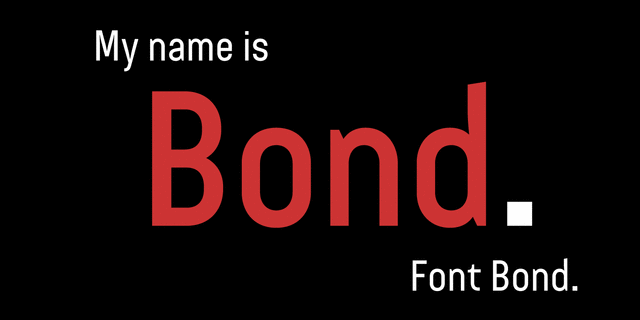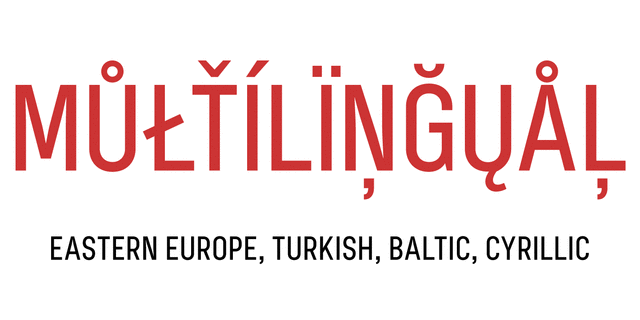
Геометрический гротеск в шести начертаниях от сверхсветлого до жирного, отлично подходит для заголовков, рекламы, плакатов. Шрифт разработал Сергей Ткаченко в 2012-2014 годах.
Ассоциации c начертанием Bond 4F MediumКачества и характер:
точный, ровный, убедительный, прямоугольный, стабильный, твердый, серьезный, надежный, уверенный, сильный, устойчивый, индустриальный, техногенный, статичный, авторитетный, городской, простой, автоматический, урбанистический, стальной, крепкий, строгий, деловой, современный, монотонный, логичный, прагматичный, практичный, искусственный, холодный, машинный, инженерный, мотивирующий, железный, крутой, железнодорожный, чертежный, амбициозный, урбанистичный, архитектурный, умный, рабочий
новости, техника, прибор, промышленность, станок, инструмент, электростанция, энергетика, завод, архитектура, наука, ремонт, дизайн, город, урбанистика, инженер, автоматика, институт, космос, небоскреб, армия, оружие, машиностроение, порт, конструктор, авиация, самолет, стройка, строительство, технологии, вагон, чертеж, железная дорога, архитектор, футбол, спорт, рабочий, рентген, дорога Стилистика: